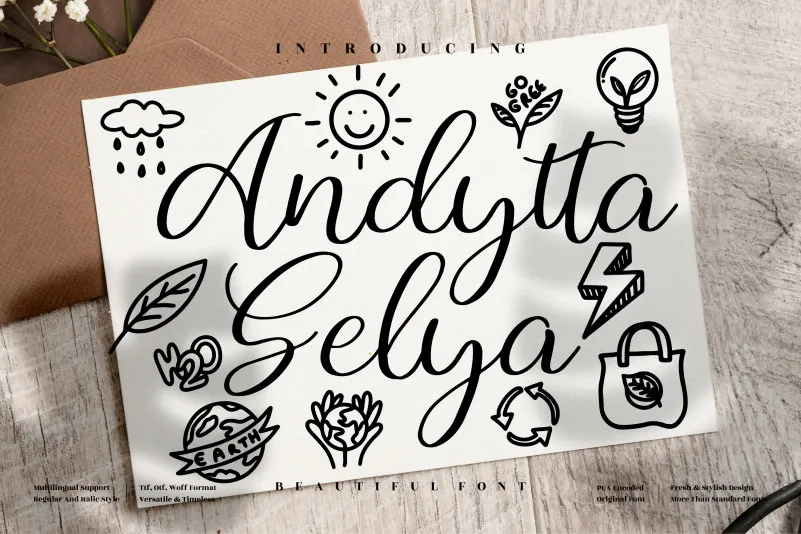
Andytta Selya Font
A Andytta Selya Font é uma elegante tipografia serifada ideal para qualquer projeto que exija um toque romântico e sofisticado. Esta fonte calligráfica é perfeita tanto para criações de logotipo, projetos de marca, design de móveis de casa, embalagens de produtos, taças, cartazes, sacolas de shopping, cartões de convite ou cartão de visitas, capas de livros e até mesmo para fotografias. Seja qual for o seu projeto gráfico que precisa de uma pitada de elegância e delicadeza, a Andytta Selya Font é sua fonte ideal. Sujeitamente adequada para eventos especiais, artefatos fotográficos ou qualquer outro tipo de trabalho artístico, esta fonte oferece um toque especial ao seu design. A equipe da perspectype criou uma combinação perfeita de elegância e rusticidade que certamente deixará seu projeto inesquecível.